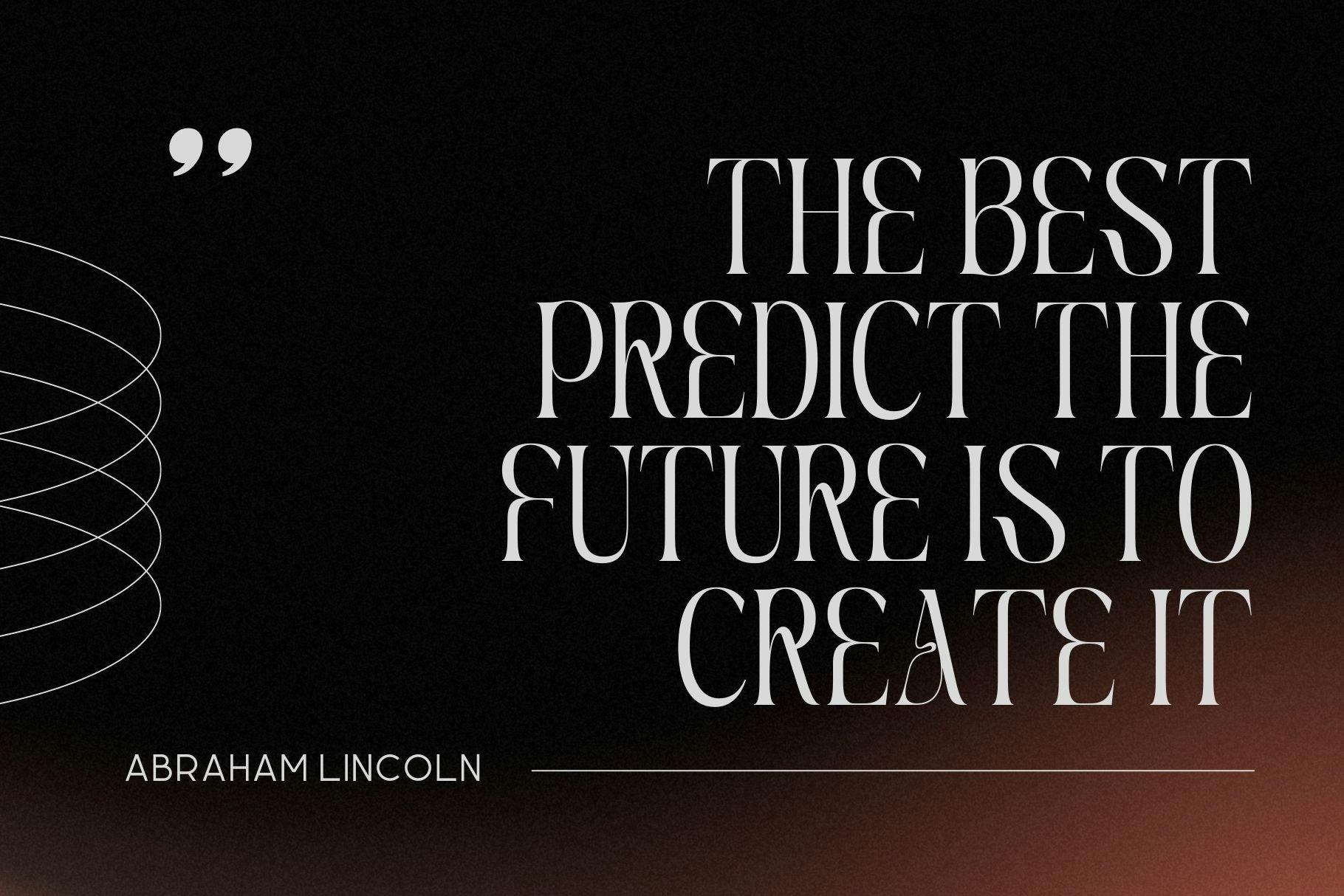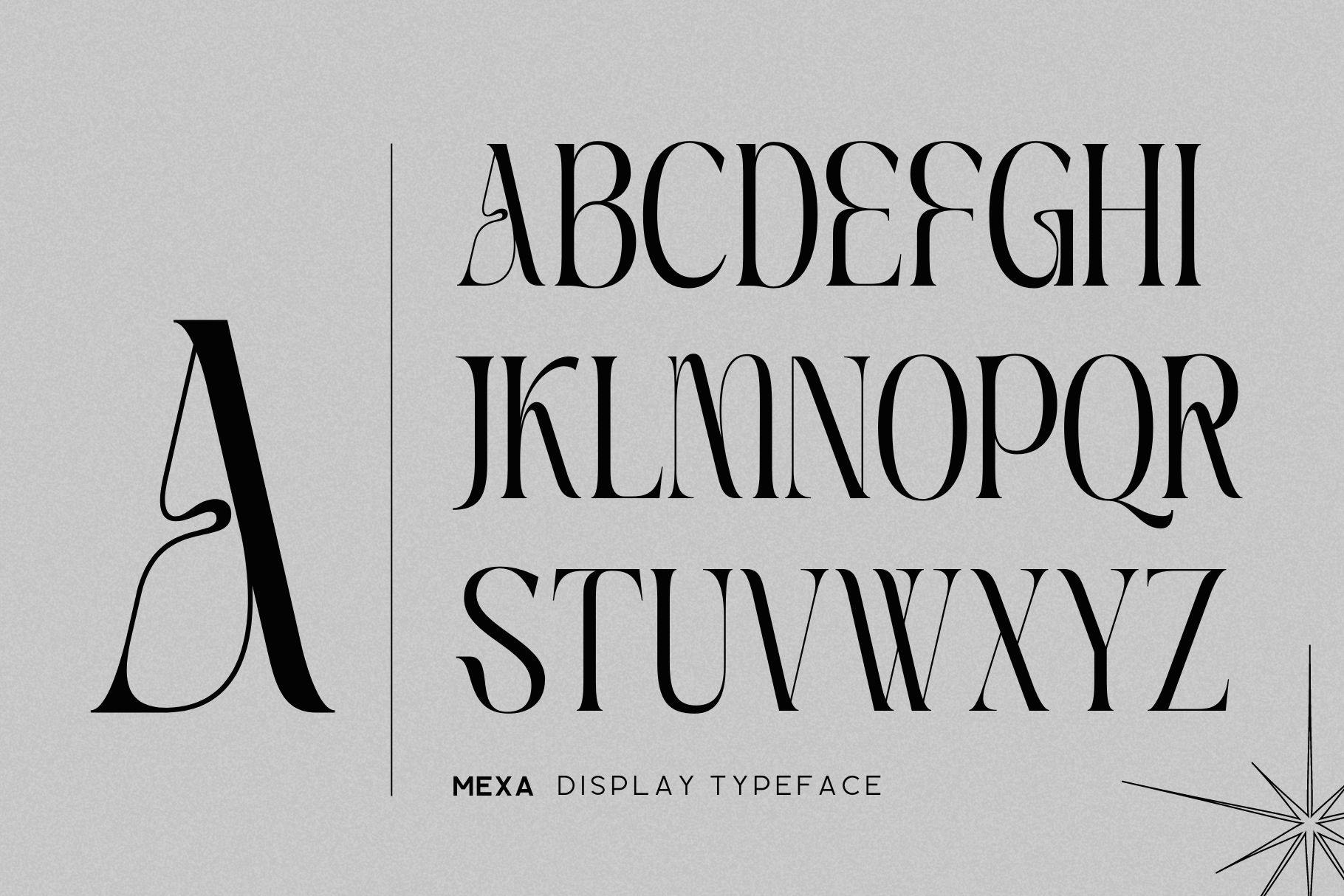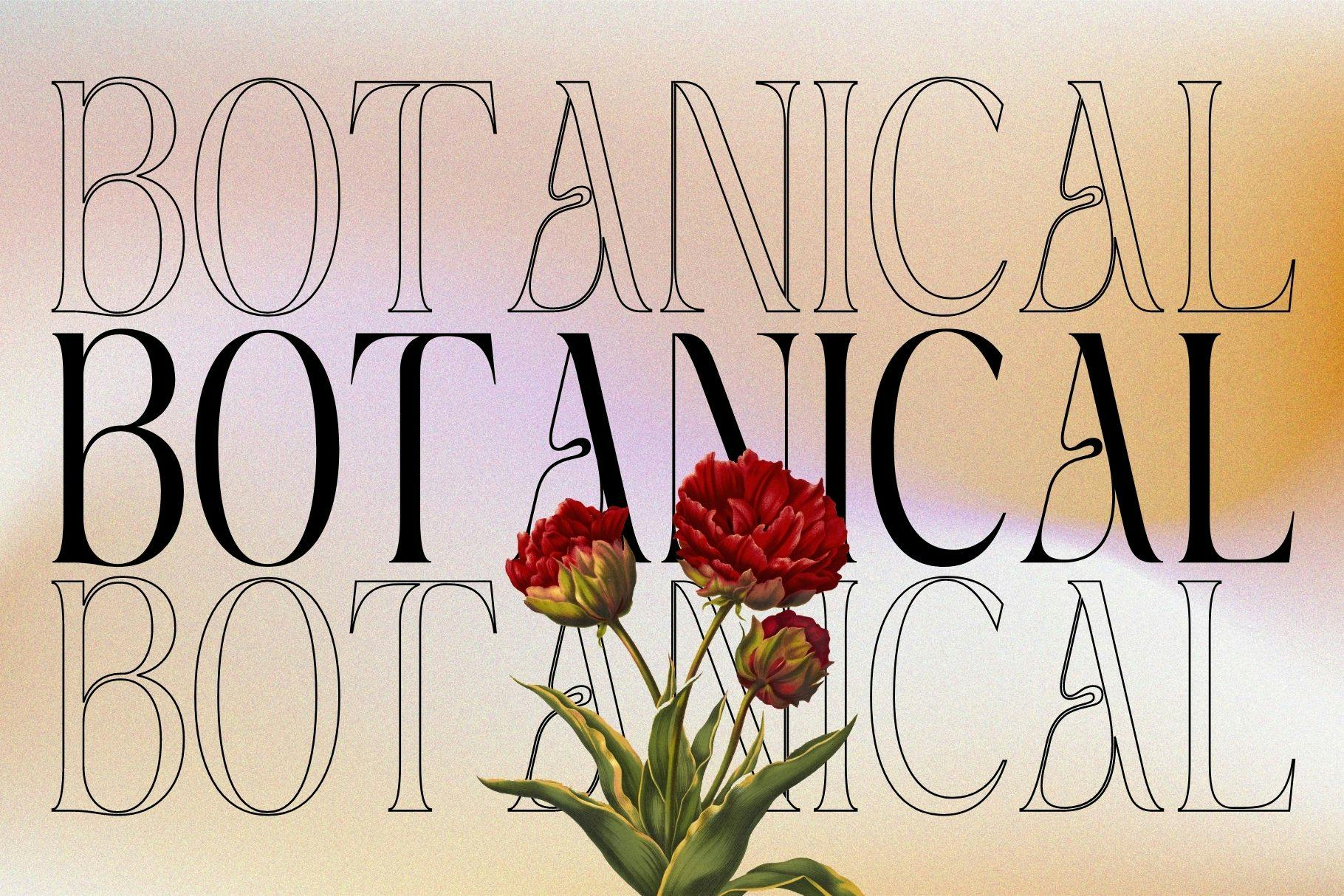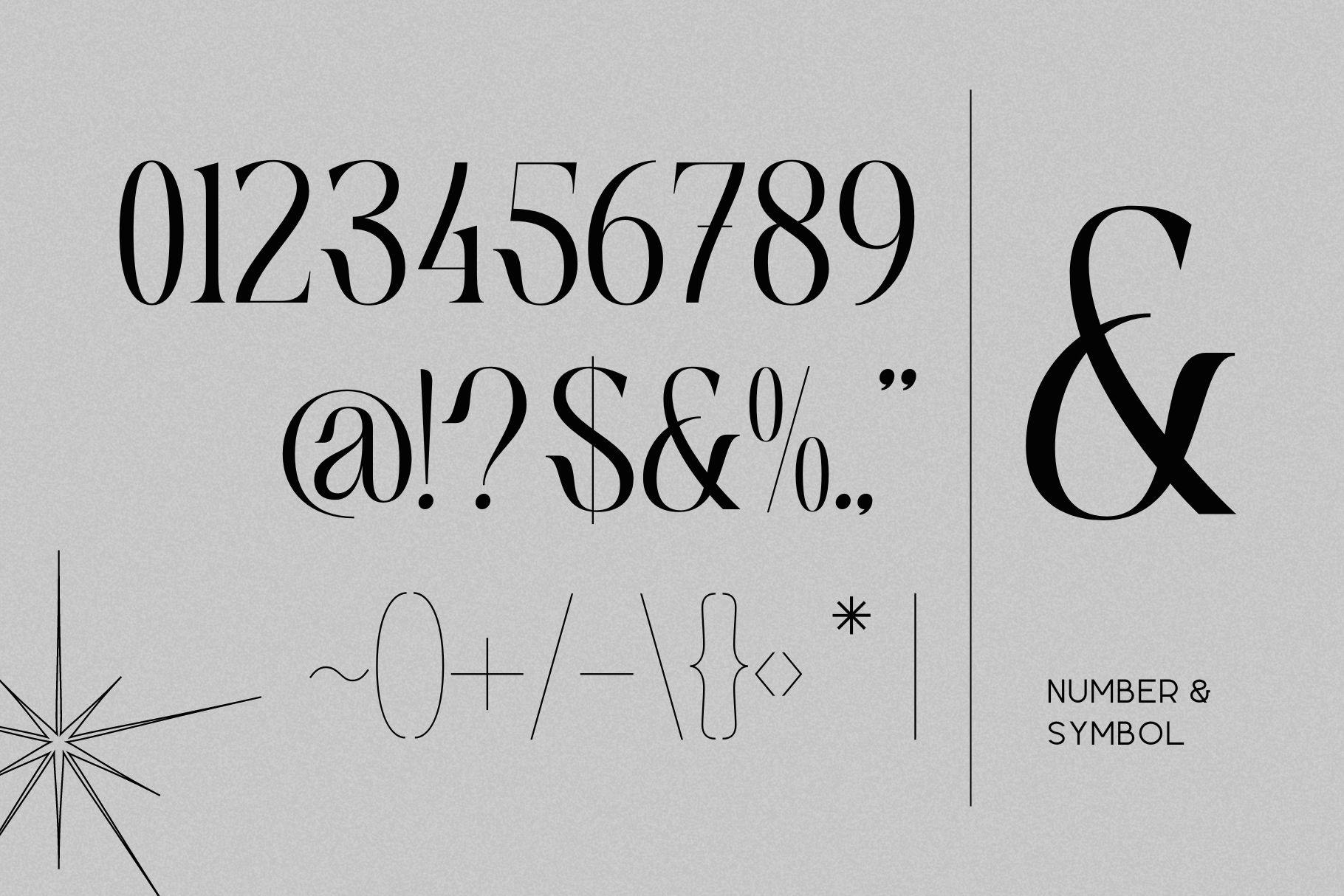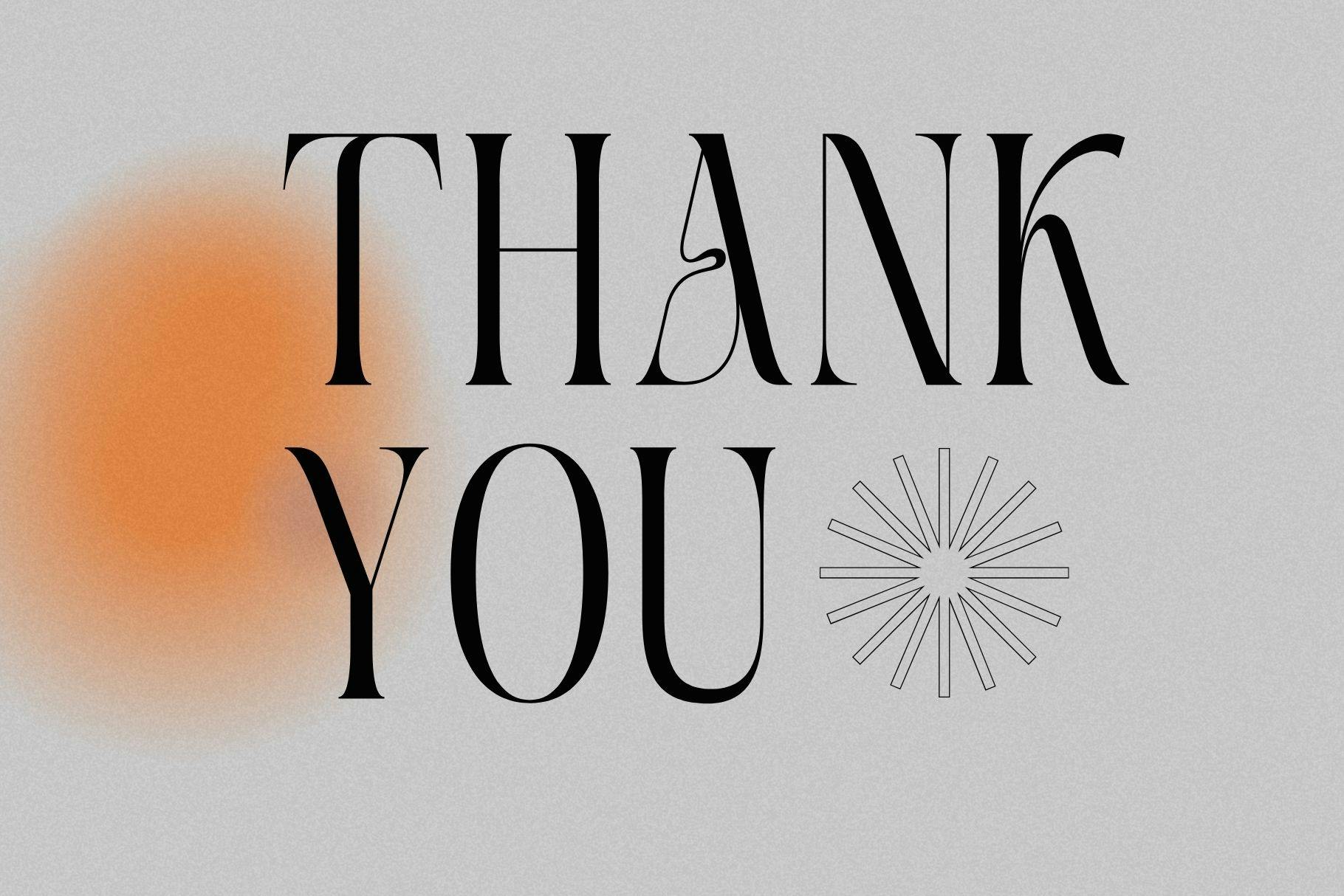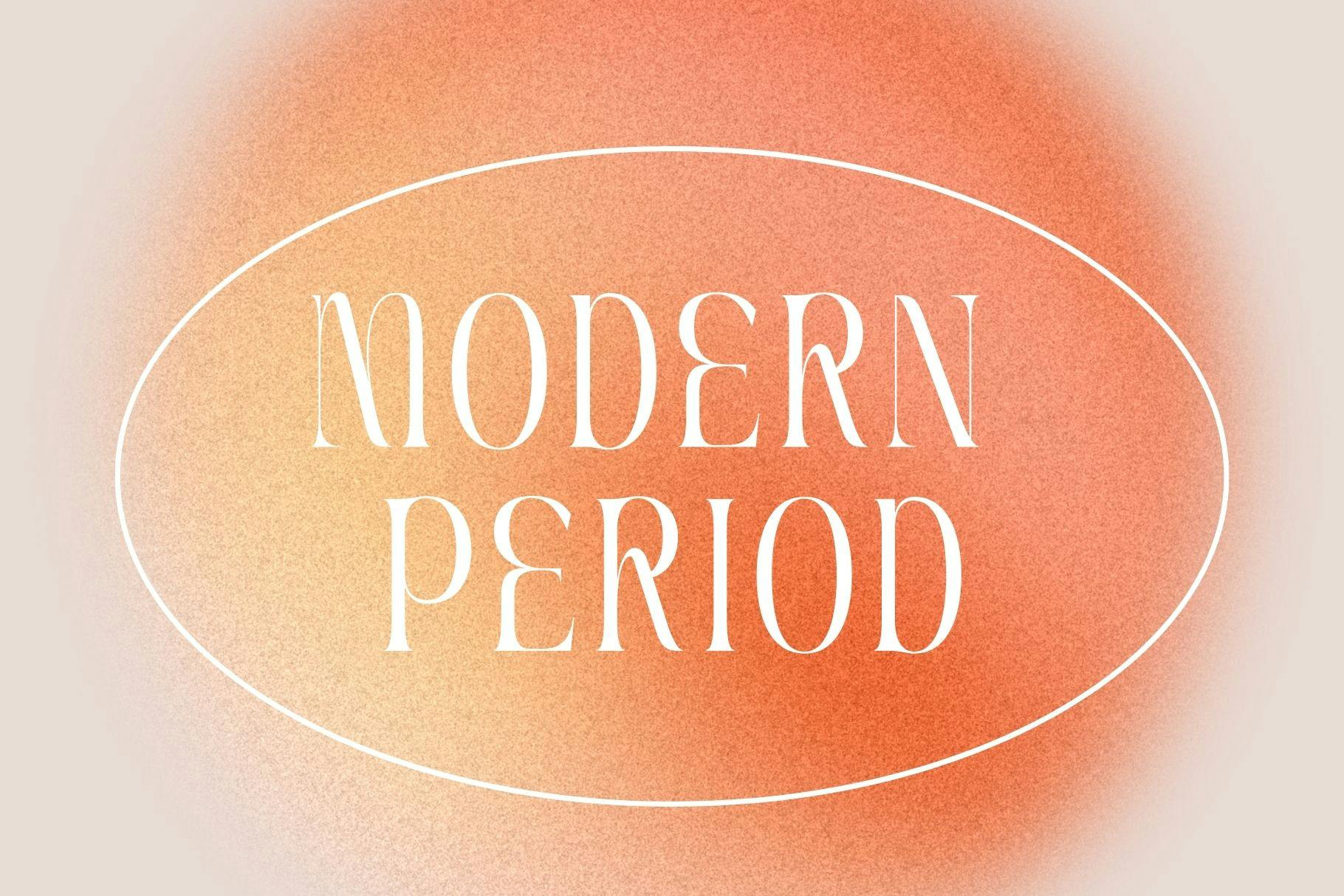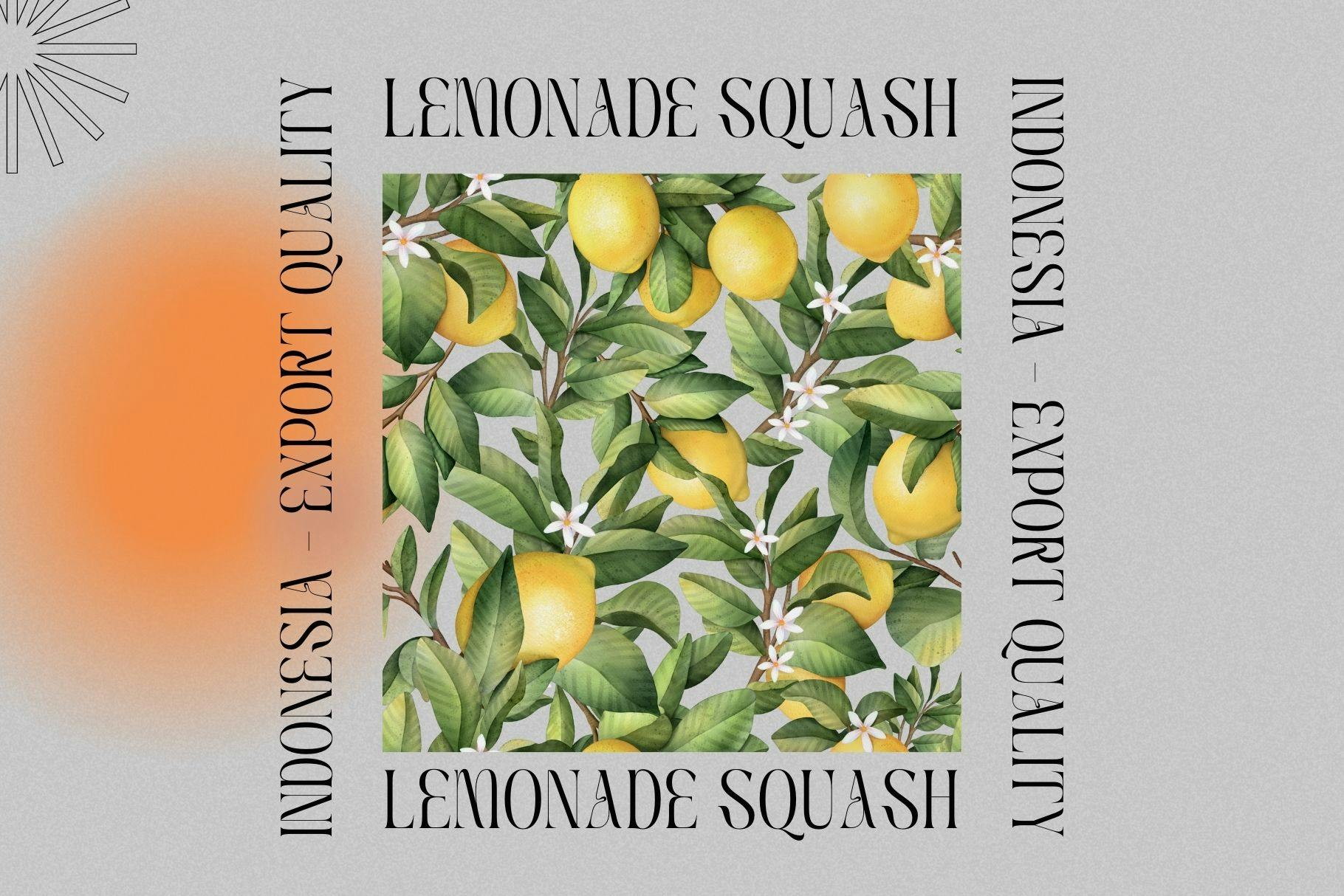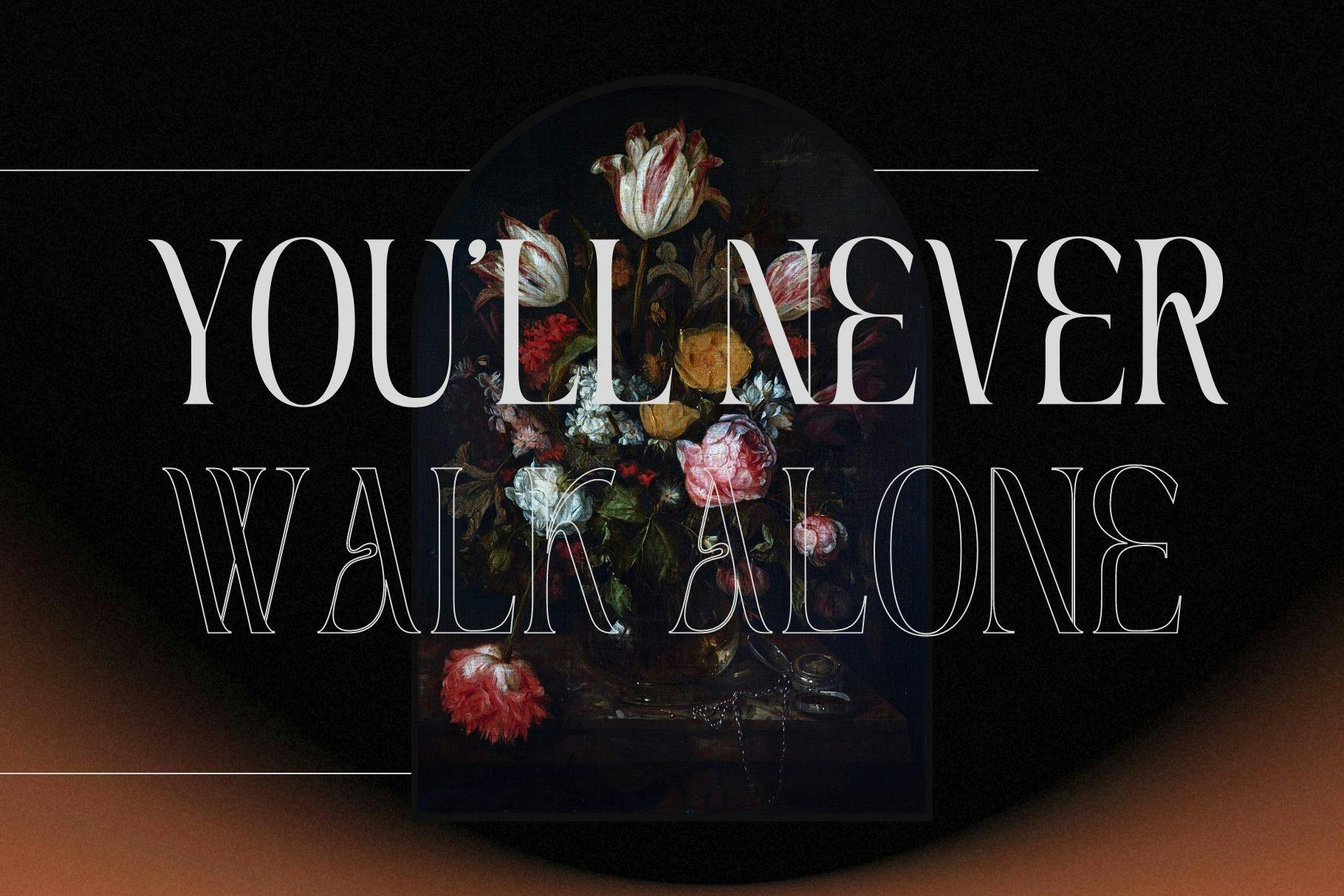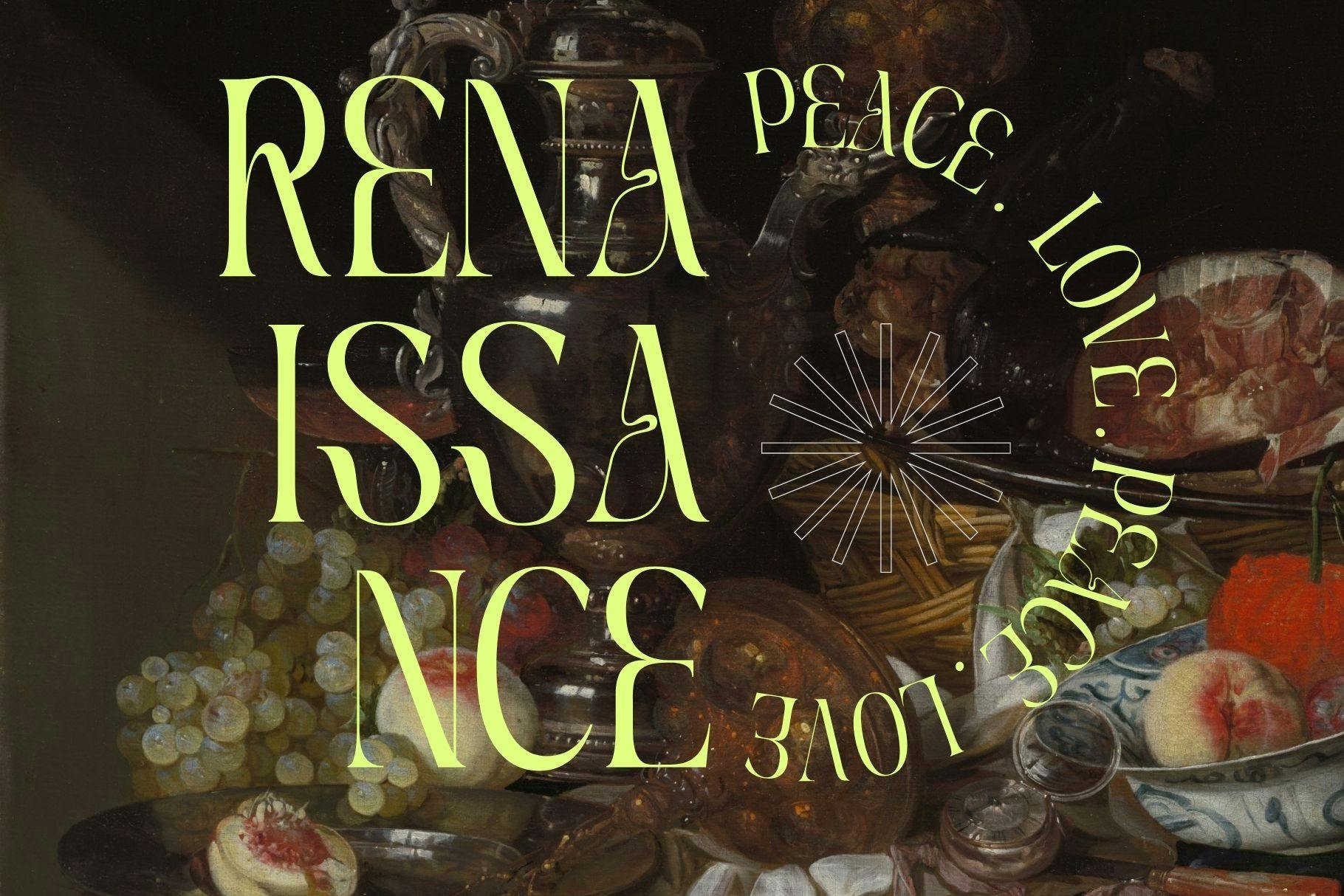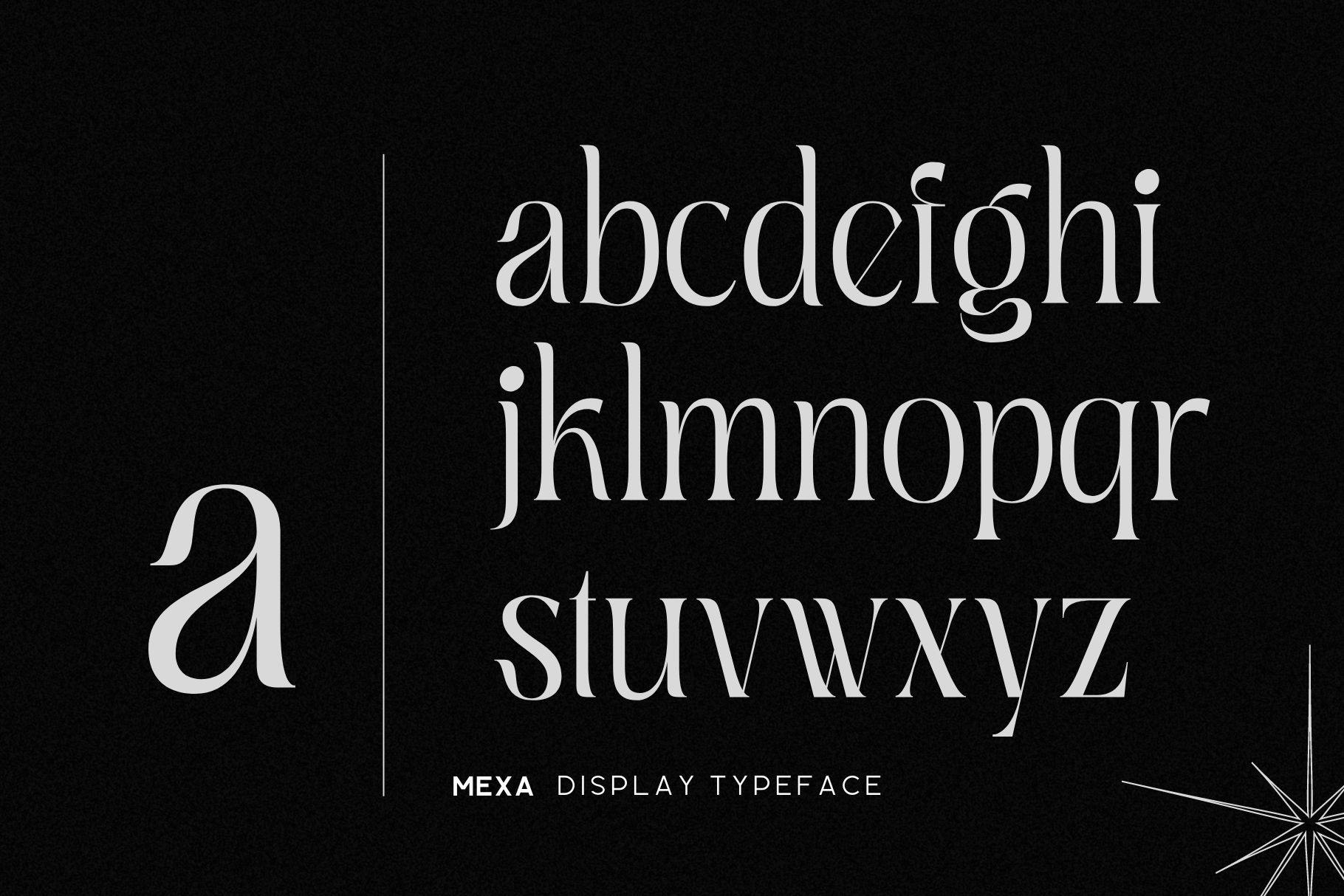
Mexa، یک فونت مدرن و از خانواده Serif است.
Mexa زیبایی و هماهنگی تایپوگرافی را برای تنوعی از پروژههای طراحی، از جمله لوگو و برندینگ، پستهای رسانههای اجتماعی، تبلیغات و طراحی محصولات ارائه میدهد.